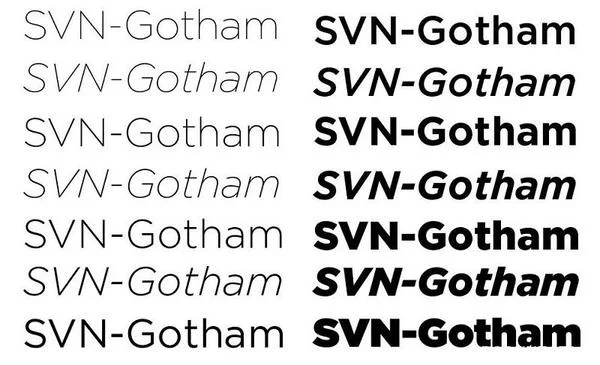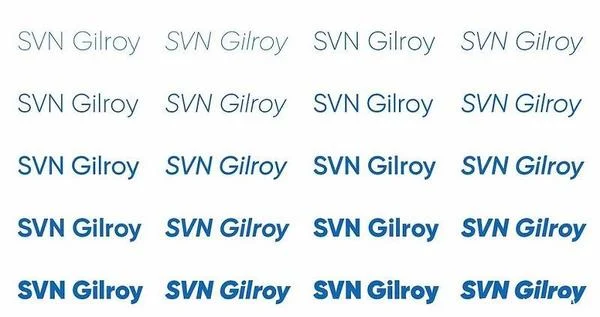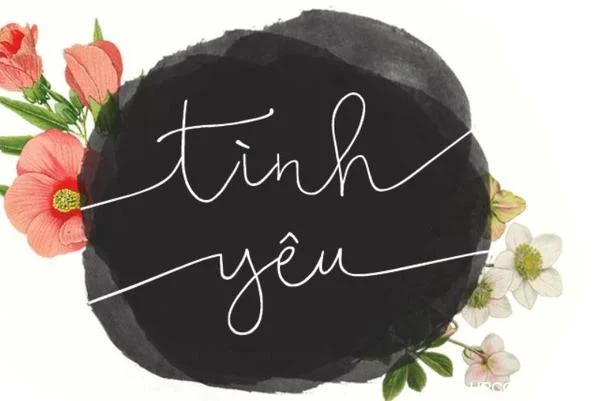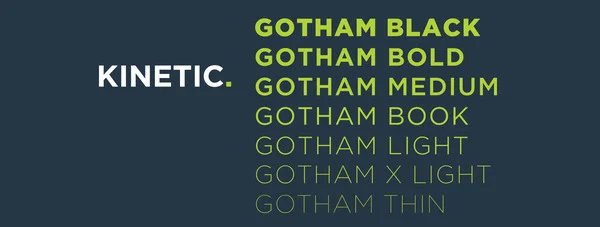
Nếu là một designer, bạn chắc hẳn đã dùng SVN Font ít nhất một lần. Font SVN là một trong những font chữ Việt hóa dùng trong đồ hoạ được các designer Việt Nam ưa chuộng và sử dụng nhiều nhất hiện nay. Nếu bạn là một “newbie" hay chỉ mới tập tễnh bước vào con đường thiết kế đồ hoạ thì bài viết này chính là dành cho bạn. Printgo sẽ giới thiệu sơ lược về font SVN và cung cấp cho các bạn link tải font SVN miễn phí ở cuối bài.
Font SVN bản Việt hoá được ra đời vào năm 2013 khi một designer đã Việt hoá font SVN. Designer này đã thực hiện Việt hoá một vài bộ font và chia sẻ miễn phí cho những designer khác trong cộng đồng của mình. Bộ font SVN là bộ font chữ rất đẹp và rất dễ để sử dụng khi áp dụng trên các nền tảng Unicode. Người dùng chỉ cần gõ theo Telex hoặc VNI mà không chỉnh bảng mã tiếng Việt thì cũng sẽ không bị lỗi font.
Bộ font SVN Gotham này thuộc nhóm Sans-serif và được bán ở dạng trả phí trên website của STYLEno.1 Fonts. Bắt nguồn từ font cách đơn giản của chữ Mỹ bản xứ, kiểu chữ này xuất hiện rất nhiều trên những cảnh quan ở khu vực đô thị như phần sơn tường, trên kính, trên tường thạch cao,…. Lấy cảm hứng từ đó, nhà thiết kế Tobias Frere-Jones đã cho ra đời bộ Font này và nó đã được tồn tại, ưa chuộng qua nhiều thế hệ khác nhau.
Gotham với vẻ đẹp đơn thuần, bình dị của mình đã tạo nên nét cuốn hút cho những dòng chữ. Kiểu chữ này rất được ưa chuộng sử dụng cho các công trình kiến trúc ở New York bởi nó có cấu trúc cơ bản, dễ thực hiện và không tốn nhiều công sức, vật liệu chuyên biệt. Kiểu chữ này không bị lỗi thời dù có vẻ ngoài đơn giản. Vì vậy, nó thường được dùng cho những thiết kế đồ họa tại những nơi công cộng, những nơi yêu cầu sự lịch sự và có tính đại chúng. Nếu muốn mua quyền sử dụng bản thiết kế này, bạn có thể truy cập Typography.com. Bộ Gotham được phát hành bởi Hoefler & Frere-Jones.
Khi sử dụng bộ font này theo font Việt hoá, bản sẽ phải trả phí cho STYLEno.1. Bộ font SVN-The Carpenter thuộc kiểu Script, được sử dụng nhiều trong các mẫu thiết kế chủ đề “Wedding” bởi vẻ thanh lịch và linh hoạt vốn có. Bộ font này cũng cung cấp cho người dùng cả những mẫu hoa văn, chữ tượng hình để hỗ trợ cho font chữ khi thiết kế.
Bộ font SVN Bellwethers này hiện đang được cung cấp miễn phí bởi STYLEno.1. Nó thuộc kiểu Script và Handwriting, Bellwethers cũng được sử dụng nhiều cho các ấn phẩm chủ đề lễ cưới giống như bộ The Carpenter.
Để sử dụng bộ font SVN Gilroy này bạn phải trả phí cho STYLEno.1. Bộ font này thuộc kiểu Sans-serif hiện đại và cũng thuộc phong cách đơn giản như Gotham. Nó cũng được đính kèm nhiều tùy chọn để người dùng có thể tùy chỉnh sao cho phù hợp với thiết kế của mình.